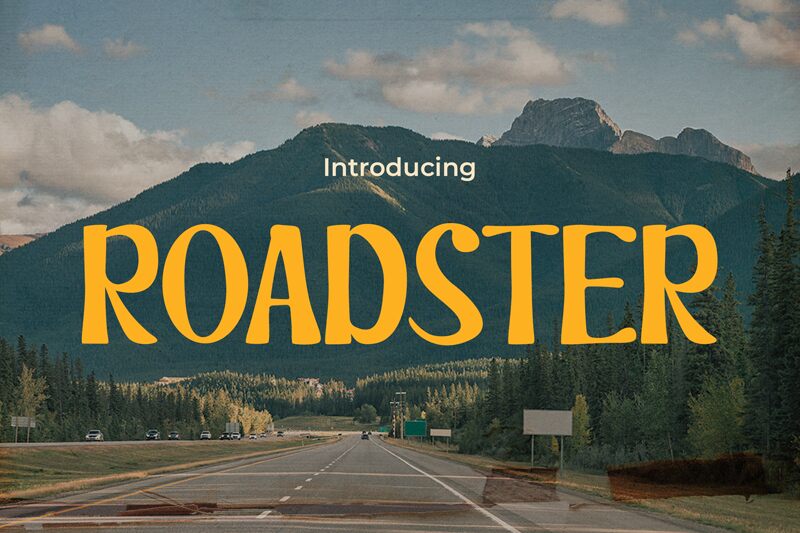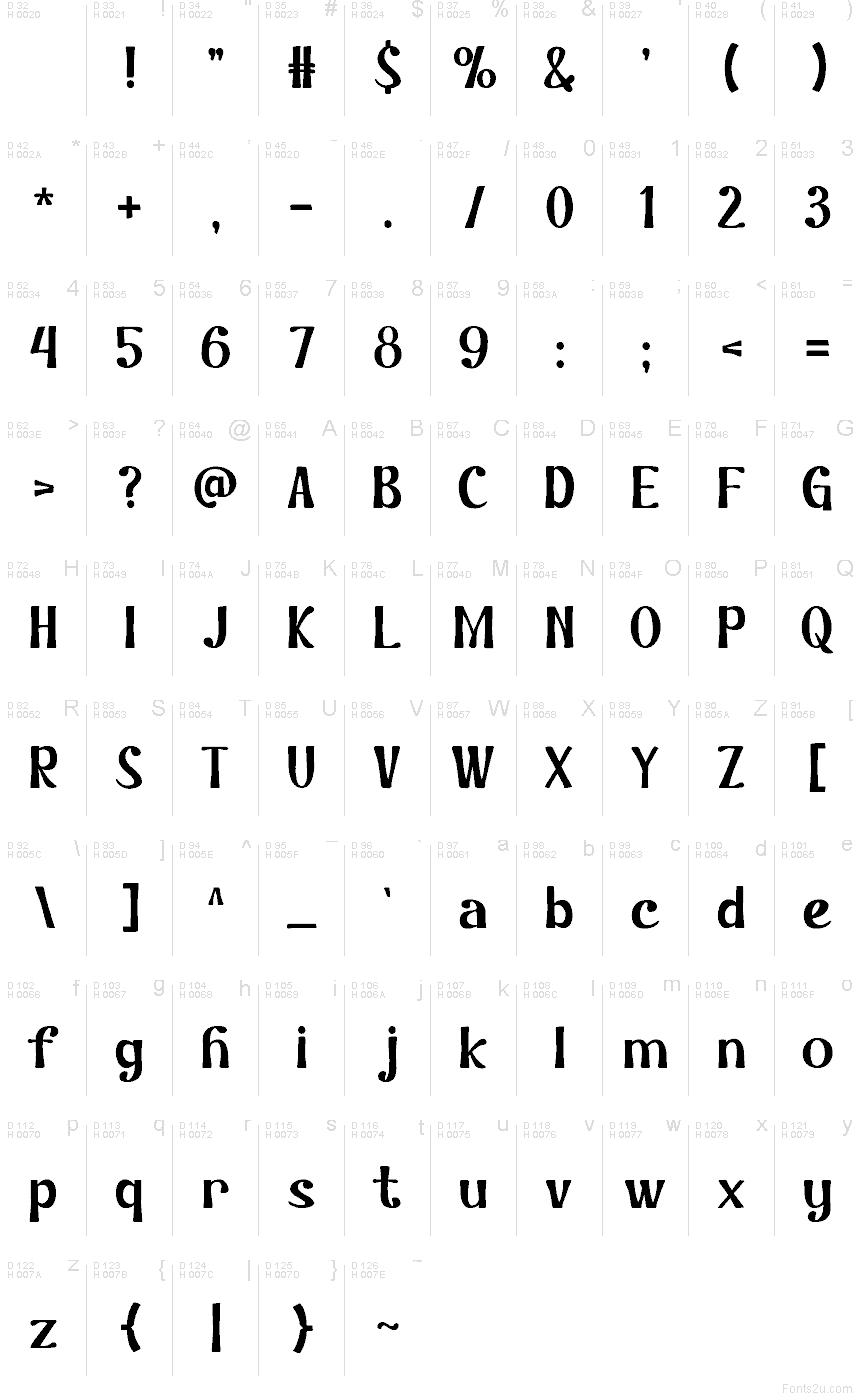
Roadster od Pinistart to darmowy, retro kroj szeryfowy typu display, utrzymany w łagodnej estetyce szyldów z lat 70. Litery łączą wysoki kontrast z zaokrąglonymi, niemal płynnymi krzywiznami oraz kilkoma wyrazistymi zdobieniami, dzięki czemu całość prezentuje się elegancko, choć z nutką teatralności.
Krój ten świetnie sprawdzi się na plakatach, w brandingu kawiarni, na okładkach płyt, opakowaniach butikowych czy w nagłówkach magazynów, gdzie ten vintage’owy sznyt jest ważniejszy niż neutralność. Jako darmowy font, ROADSTER pasuje także do krótkich tytułów i monogramów, ponieważ smukły rytm i zamaszyste krzywizny nadają nawet pojedynczym literom mocny, charakterystyczny klimat tamtej epoki.